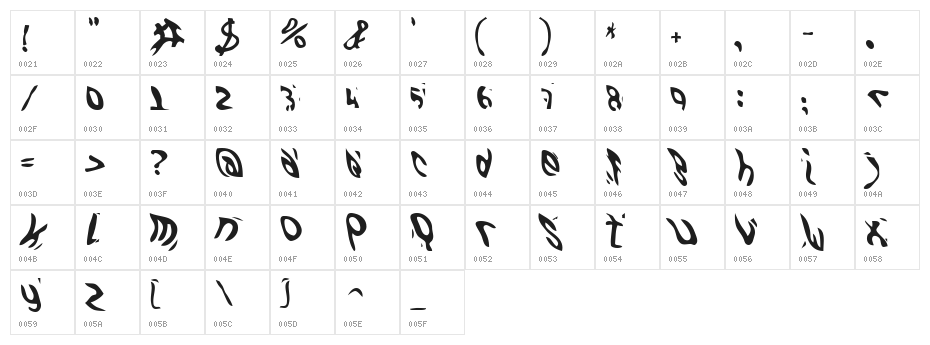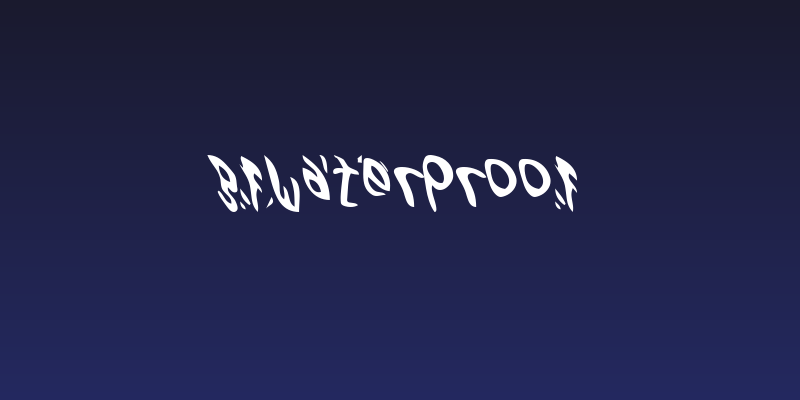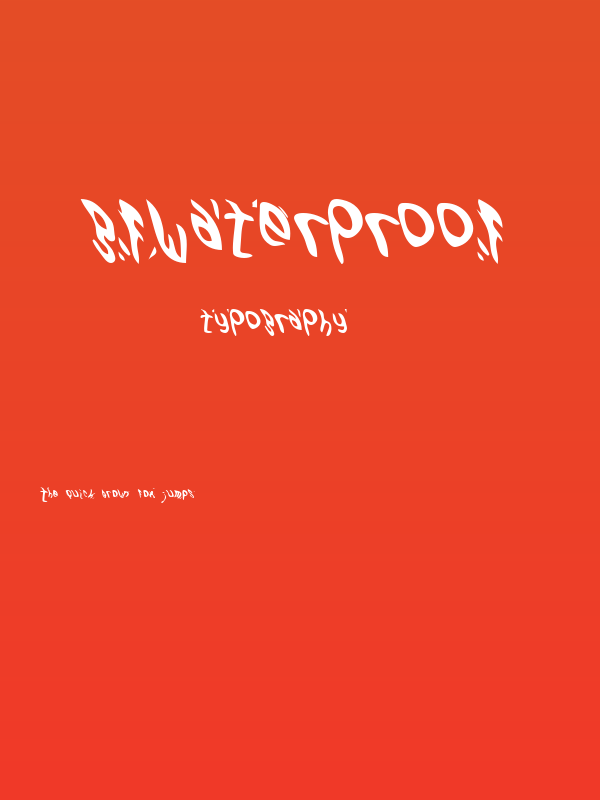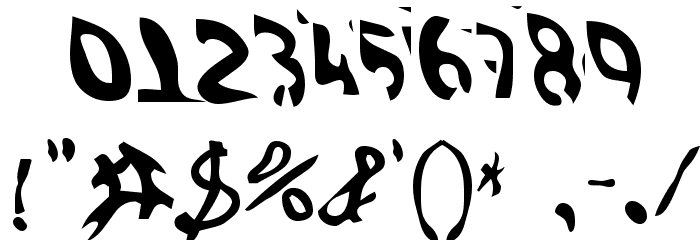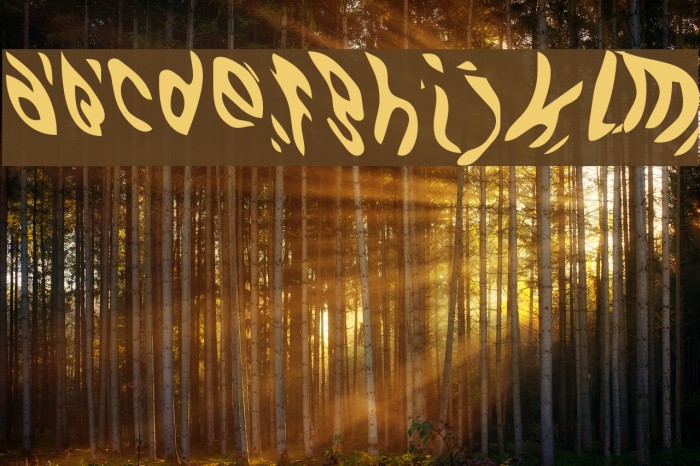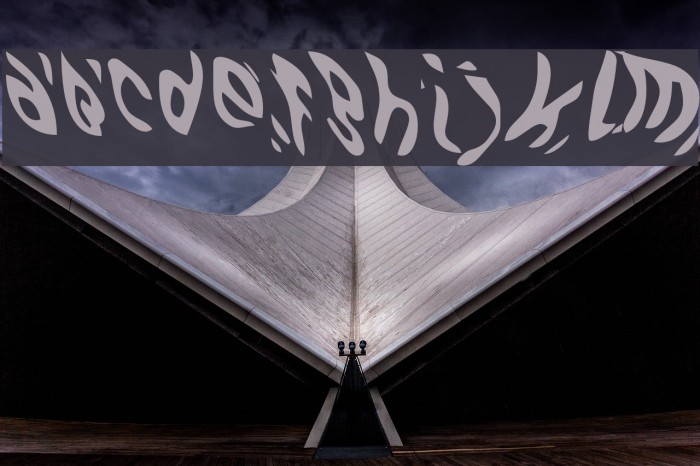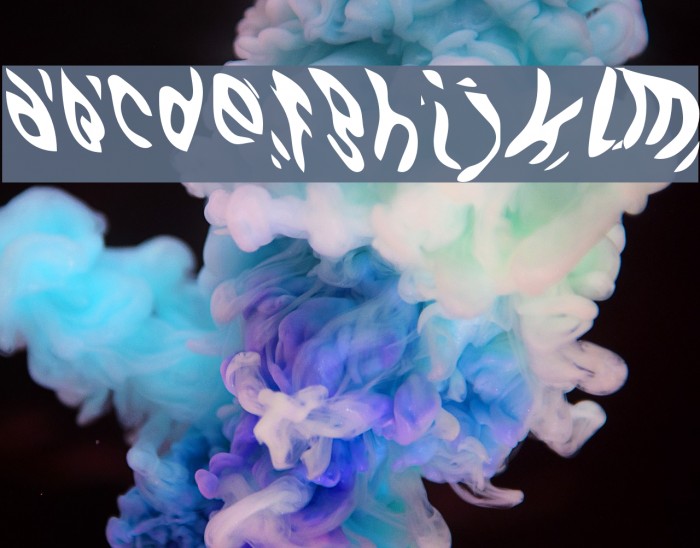
GFWaterproof Font
| Anwendungsfall | Headlines, Logos, Artistic designs |
| Vorgeschlagene Projekte | Ideal for creative projects such as album covers, posters, or branding for artistic ventures. It can also be used in digital art or experimental design projects. |